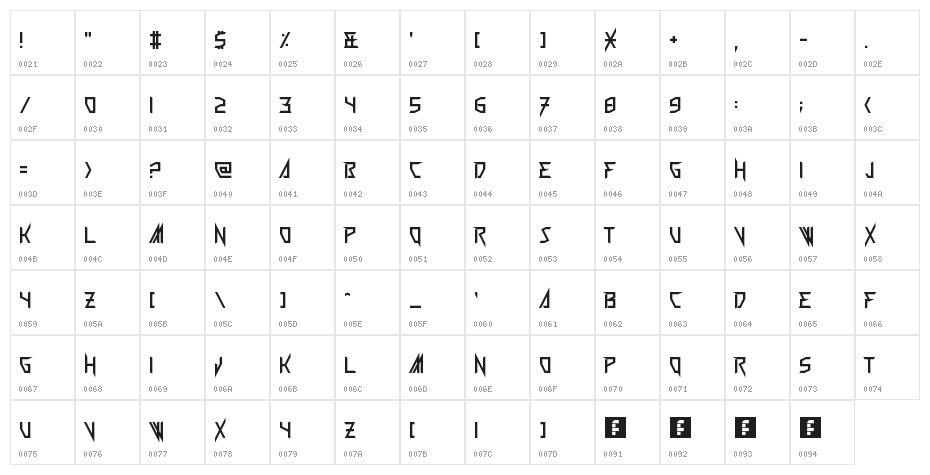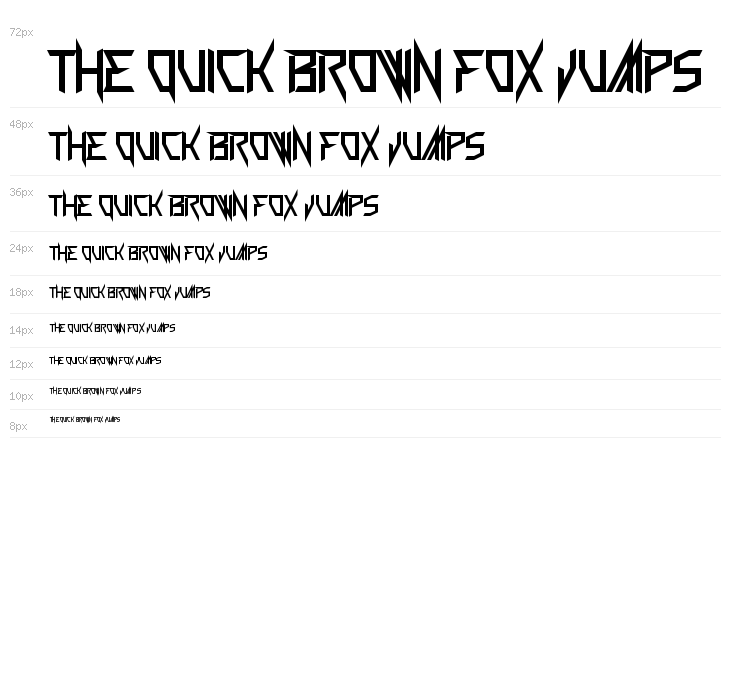
Wickermanor Regular Font
| مشاريع مقترحة | Ideal for sci-fi themed projects, video game titles, posters, and branding that requires a modern and bold aesthetic. |